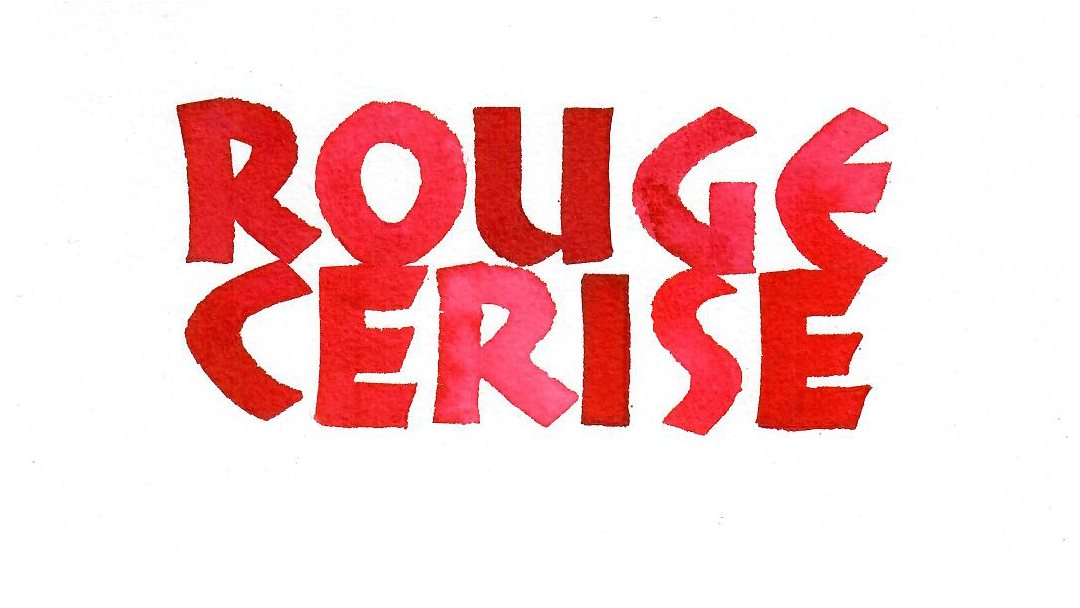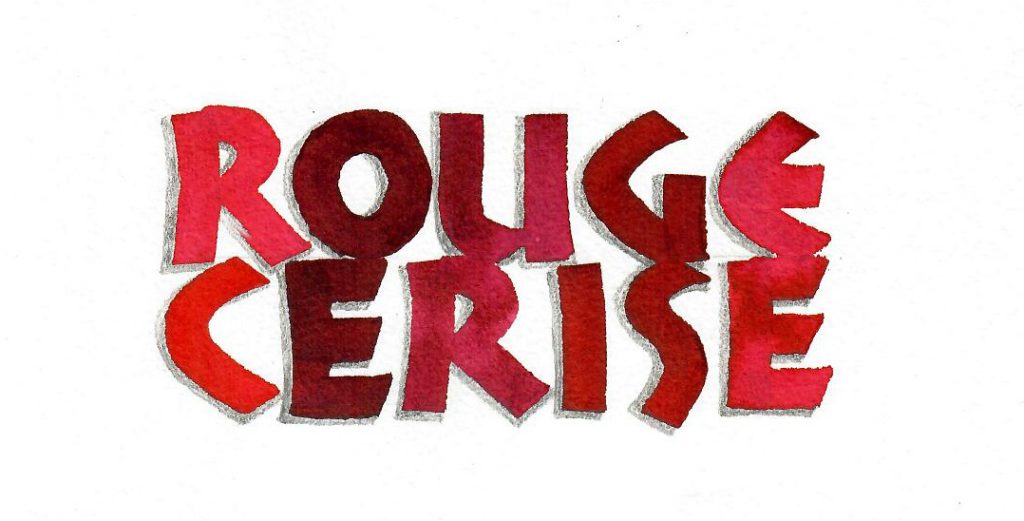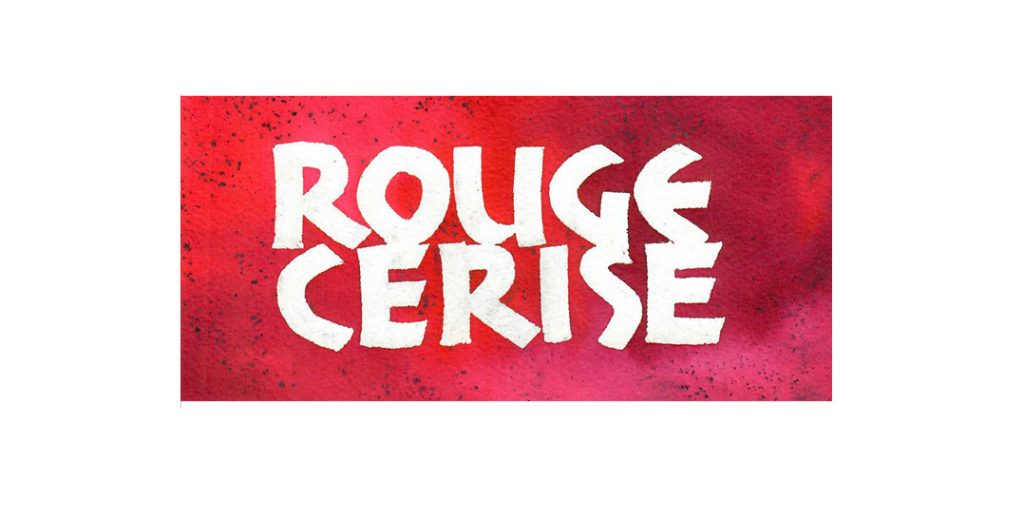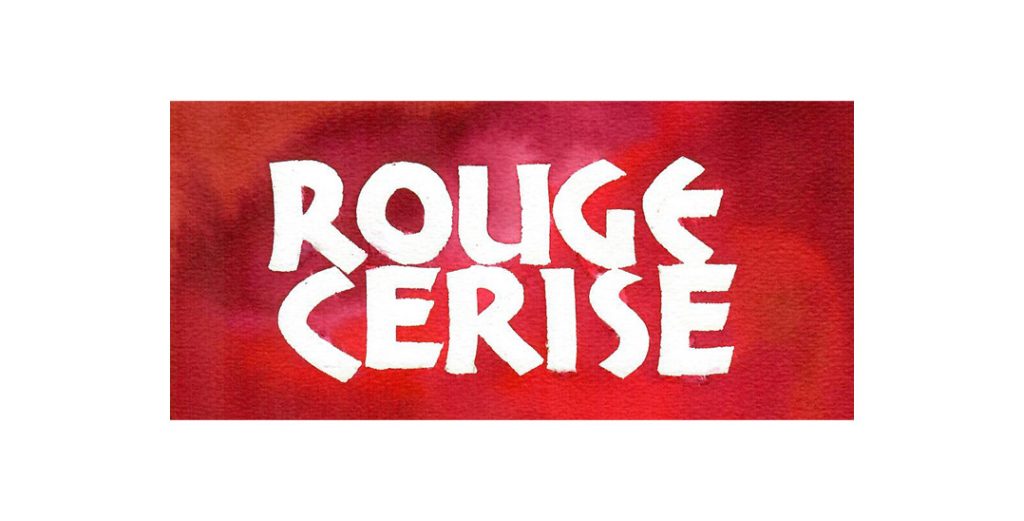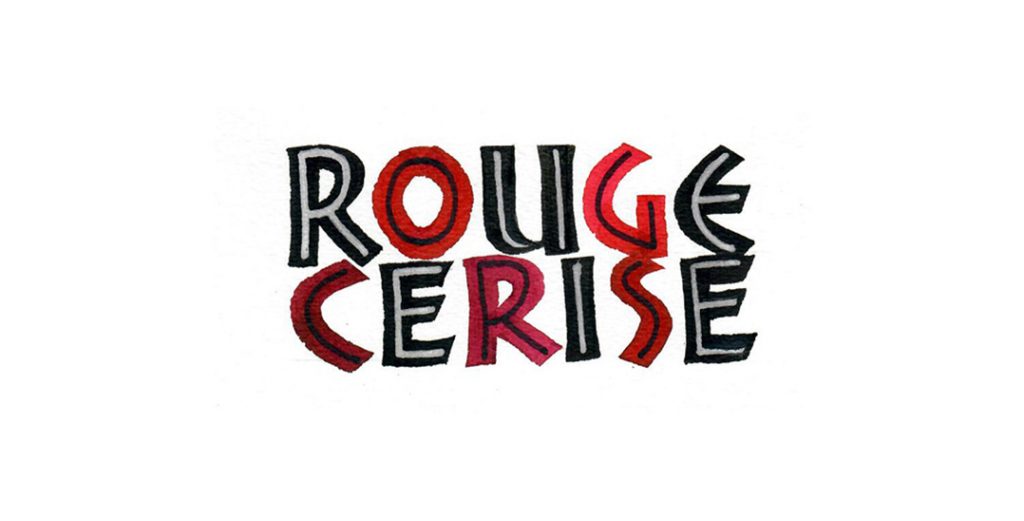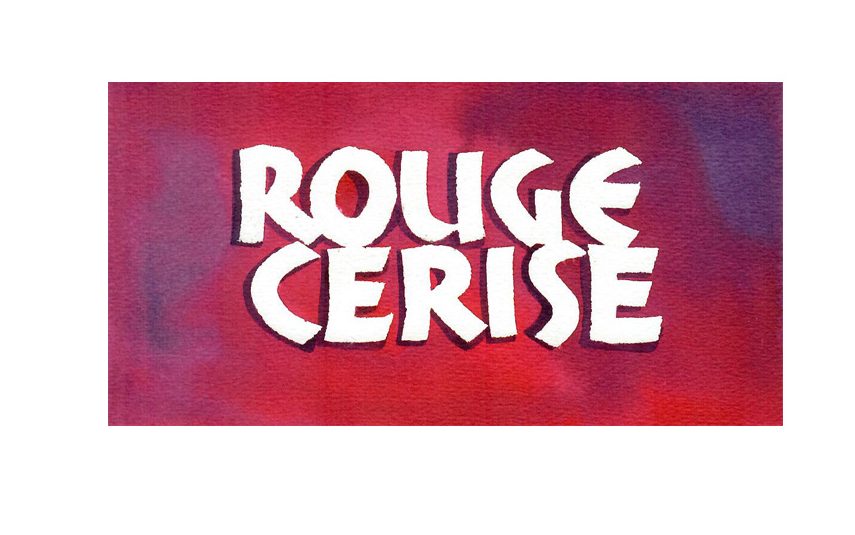
L’article de la semaine dernière sur la Neuland vous a beaucoup plus et je m’en réjouis. Je partage avec vous et sans blabla quelques variations expérimentées ce week-end, à partir d’une même compo simple.
J’ai travaillé sur du papier aquarelle ordinaire, avec de l’encre aquarelle Colorex et un automatic pen taille 4.
Neuland – Encre Aquarelle Colorex
Neuland – Encre aquarelle et ombrage avec un crayon graphite
Neuland – Drawing Gum et encre aquarelle
Neuland – Encre aquarelle et marqueur à l’intérieur des lettres
Neuland – Encre aquarelle avec un effet oxydé obtenu par grattage de graphite
Neuland – Drawing Gum, fond avec des encres aquarelles avec un effet oxydé
Neuland – Encre aquarelle et fineliner
Neuland – Drawing Gum et encre aquarelle
Neuland- Drawing Gum et ombrage au pinceau
Faire ces variations m’a donné encore plein d’idées pour la suite… à suivre donc !